Строчная «я» в рукописном шрифте: петля, просвет и узнаваемость
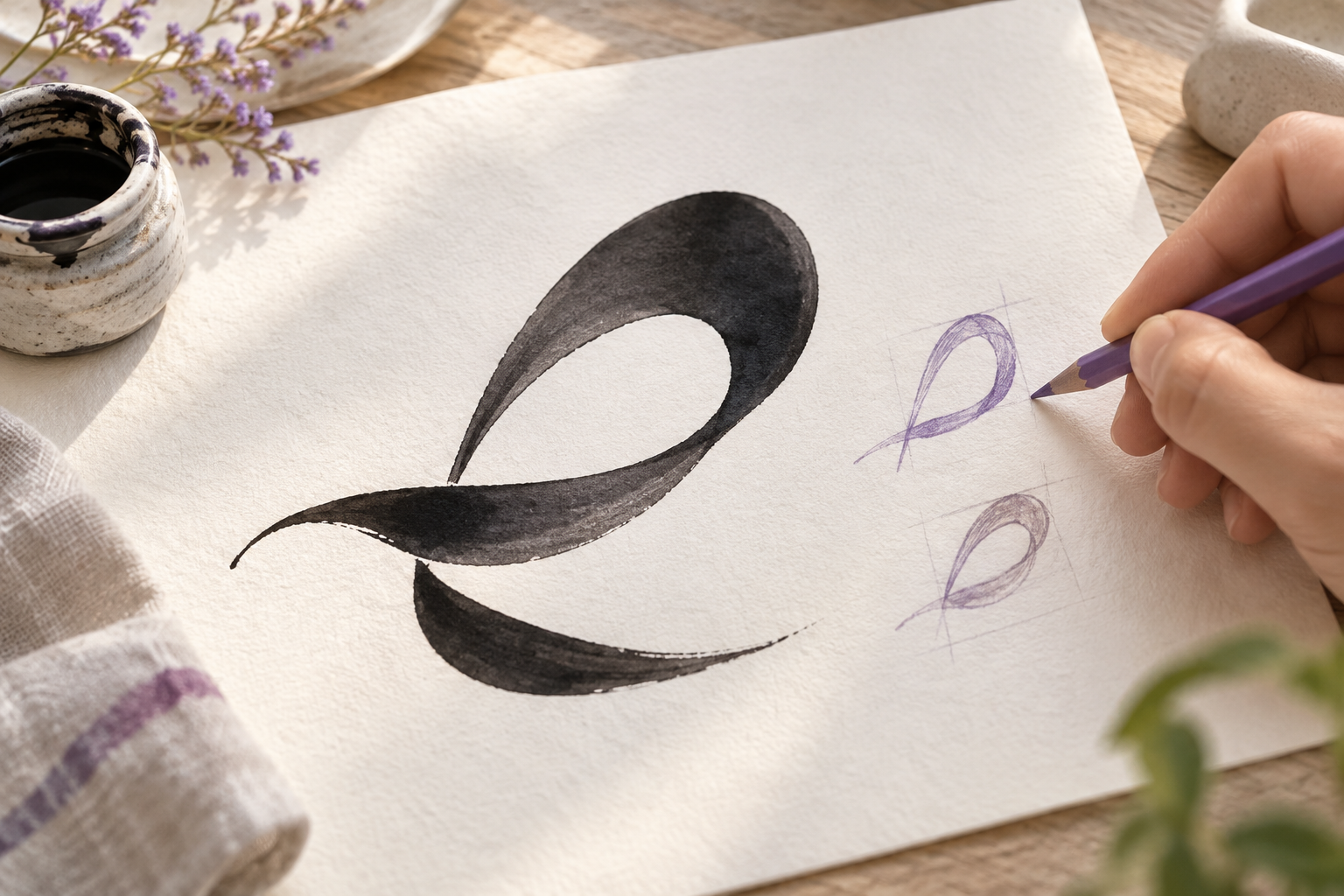
Строчная «я» должна оставаться узнаваемой даже в выразительном рукописном шрифте. Для этого недостаточно просто отразить латинскую R: важны направление основного силуэта, внутренний просвет, характер соединения и длина нижнего штриха. Ниже — способ нарисовать знак, сравнить его с соседними буквами и проверить в реальных словах, а не только отдельно на увеличенном экране.
Сначала определите, какую именно «я» вы рисуете
Прежде чем строить контур, решите, где и как будут использовать шрифт. В современном русском наборе строчной букве «я» соответствует отдельный символ Unicode U+044F; это описание кодовой точки, а не готовая инструкция по рисунку глифа (таблица Unicode). Обычная печатная форма, курсивная форма и конкретное авторское начертание могут различаться. Поэтому не копируйте первый попавшийся образец и не считайте, что формальное соответствие знаку само по себе гарантирует узнаваемый рисунок.
Соберите три ориентира: форму строчной «я», характер остальных строчных букв вашего алфавита и образец того почерка, который вы хотите сохранить. Если источник — собственный почерк, найдите букву в нескольких словах и выпишите, что в ней повторяется. Возможно, вы каждый раз начинаете с овала; возможно, нижний штрих уходит назад дугой; иногда форма меняется только при соединении с последующей буквой. Отделите постоянный признак от случайного движения руки.
Задайте ограничение по применению. Для подписи на открытке допустим более причудливый силуэт, если слово прочитывается в контексте. Для длинных заметок, учебных материалов или фамилий важнее стабильное чтение в непрерывном тексте. Это не значит, что все рукописные шрифты должны быть нейтральными: задача — решить, какой элемент будет выражать характер, а какие элементы удержат идентичность буквы.
Наконец, решите, будет ли в вашем проекте один рисунок «я» или несколько вариантов. Для базового набора обычно важнее сначала закончить один надёжный глиф. Альтернативу имеет смысл рассматривать, если она нужна для особого почеркового ритма и может быть показана последовательно; случайное различие между копиями буквы усложнит проверку. Если в шрифте предусмотрены контекстные варианты, убедитесь, что основной знак читаем и без переключения на них.
Разложите форму на признаки
Не сравнивайте знак только с латинской буквой R или с перевёрнутым образцом на экране. У «я» есть собственная кириллическая логика. Для черновика удобно разделить рисунок на четыре зоны:
- Верхняя часть — где начинается силуэт и как он входит в основной корпус строчной буквы.
- Поворот — место, где внешний контур меняет направление и образует верхнюю чашу или петлю.
- Просвет — внутренняя форма, её ширина и положение относительно оси.
- Нижний штрих — диагональ или дуга, которая задаёт характер завершения и связывает знак с соседями.
Нарисуйте несколько вариантов, меняя по одному признаку. Например, оставьте неизменными высоту и наклон, но сделайте просвет то уже, то шире; затем сравните два вида нижнего штриха. Если менять всё одновременно — наклон, ширину, петлю и толщину — будет трудно понять, какая правка действительно помогла.
В рукописном алфавите особенно легко потерять читаемость, когда нижний штрих превращают в длинную декоративную петлю. В изоляции такой жест может выглядеть изящно, но в строке он способен слипнуться с соединением следующей буквы или сделать «я» похожей на соседнюю форму. Сначала закрепите устойчивый каркас, затем добавляйте почерковую интонацию в пределах этого каркаса.
Найдите баланс петли и просвета
Петля сообщает характер и помогает сделать глиф родственным округлым буквам, но слишком замкнутый или тесный просвет может превратить знак в тёмное пятно. Оцените пространство не только по площади. Важно, где оно расположено: смещённый вверх или в сторону просвет может сделать букву нервной, а слишком геометричный — чужой по отношению к мягкому почерку.
Практический приём: нарисуйте букву крупно, затем заполните контур ровным тоном и посмотрите на внутреннюю белую область. После этого уменьшите знак примерно до того размера, в котором он будет использоваться. Если отверстие исчезает, не обязательно сразу утончать штрихи. Попробуйте немного раскрыть поворот, сдвинуть место стыка или ослабить изгиб, который перекрывает светлое поле.
Проверяйте форму в двух режимах:
- Контурный вид показывает, нет ли случайной неровности, излома или лишнего узла.
- Чёрное пятно помогает увидеть, не забит ли просвет и не утяжелён ли один угол.
Сравнивайте соседние варианты рядом, а не по памяти. Сохраните контрольную форму до каждой существенной правки. Так проще решить, стало ли чтение лучше, и вернуться назад, если декоративный вариант потерял ясность.
Согласуйте «я» с ритмом строчных букв
Даже узнаваемая отдельно «я» может выглядеть чужой в алфавите. Сверьте высоту корпуса, наклон, ширину и толщину с несколькими близкими по движению формами. Для начала подойдут «а», «б», «в», «р» и «у»: это не набор обязательных пар для любого шрифта, а удобные соседи, с которыми можно проверить внутренние пространства, петли, выходы штрихов и нижние элементы.
Строчную «я» легче сделать узнаваемой, если сначала зафиксировать конструктивные признаки, а затем отдельно согласовать петлю, просвет и нижний штрих с ритмом алфавита. Сравнивайте варианты по одному изменению и читайте букву в словах до и после уменьшения. Если создаёте собственный рукописный шрифт, подготовьте полный набор в Fontgenerator, а форму «я» проверьте в тех фразах, для которых шрифт предназначен.